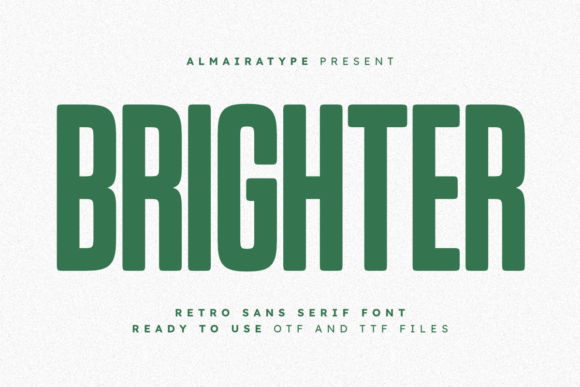
Brighter
Brighter – La police vintage qui fait briller votre création
Vous cherchez une typographie qui allie nostalgie rétro et modernité audacieuse? Brighter, la police sans-serif rétro, est votre nouvel allié. Conçue pour dominer l’affiche, le logo ou une série de t-shirts, cette police offre une lisibilité exceptionnelle tout en injectant un style unique à vos projets.
Pourquoi Brighter est indispensable pour les créateurs
- **Structure haute et solide** – Capte immédiatement l’attention sans sacrifier la clarté.
- **Éléments arrondis doux** – Ajoute une touche chaleureuse inspirée des années 70 et 80.
- **Polyvalence** – Parfait pour les designs de t-shirts, les appareils rétro et les identités de marque.
- **Compatibilité POD** – Idéal pour les entrepreneurs Print on Demand qui exigent un rendu de haute qualité sur vêtements, mugs ou casquettes.
- **Facile à intégrer** – Fonctionne sans problème avec les machines Cricut et Silhouette, pour les amateurs de craft et de DIY.
Applications majeures de Brighter
Que vous travailliez sur un affiche accrocheuse, un packaging de produit ou un logo d’entreprise, Brighter se distingue par son impact visuel. Ses lignes épurées et son caractère « bold » en font un choix privilégié pour :
- Les t-shirts tendance voulant se démarquer dans la foule.
- Les affiches de concerts nostalgique.
- Les brandings de cafés et boutiques vintage.
- Les projets de scrapbooking et de papercraft.
Conclusion – Faites briller votre marque avec Brighter
En intégrant Brighter dans votre arsenal typographique, vous offrez à vos clients une lecture fluide et un look inoubliable. Cette police est la garantie d’un impressionnant rendu visuel, qu’il s’agisse d’un logo, d’un poster ou d’une opération de Print on Demand. Donnez à vos créations la présence forte et le charme rétro qu’elles méritent, et laissez Brighter transformer vos idées en succès.